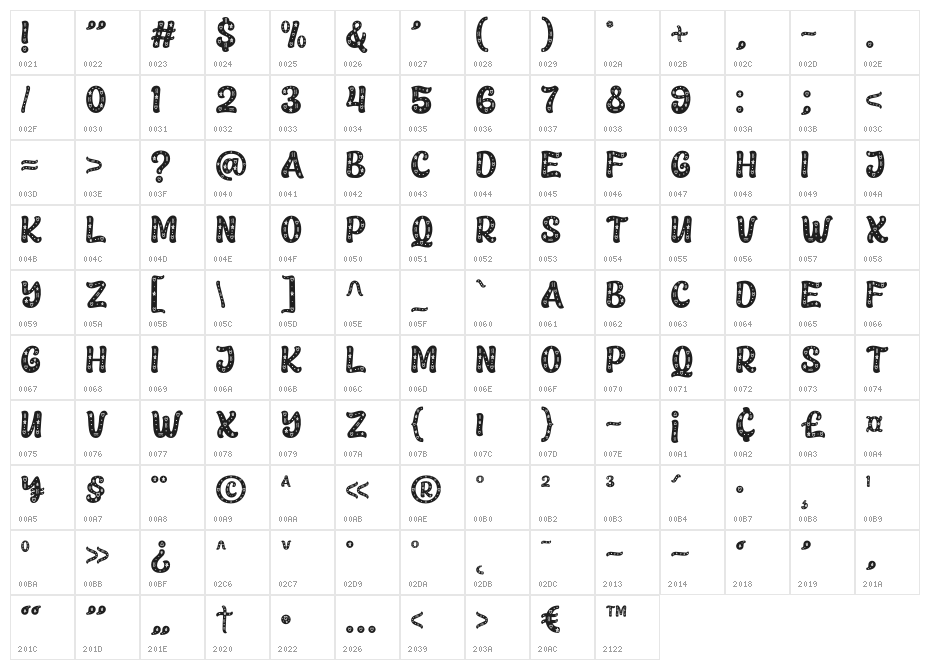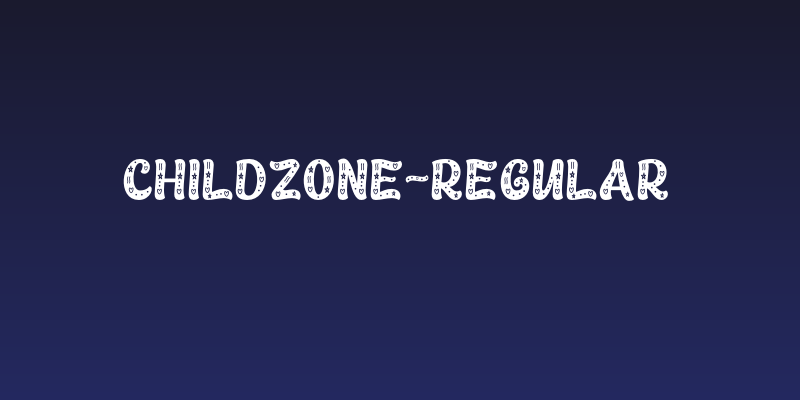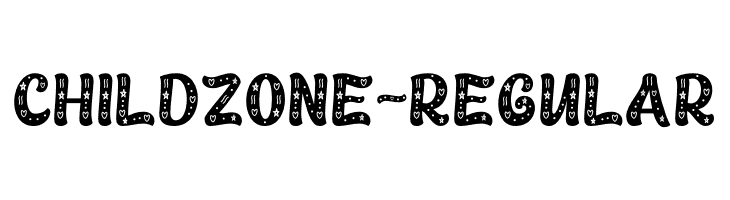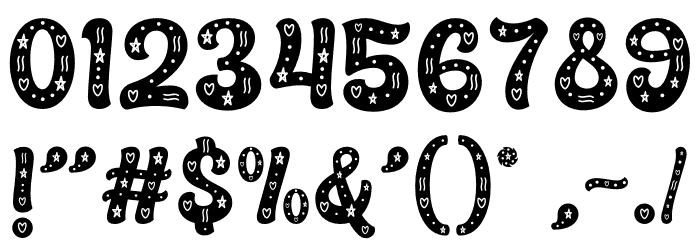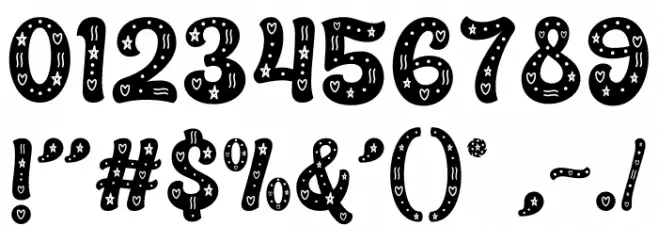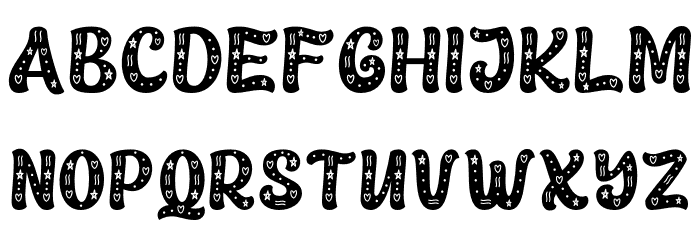
Childzone-Regular Font
| النمط العام | Playful, Whimsical |
| حالة الاستخدام | Headlines, Logos, Children's materials |
| مشاريع مقترحة | Ideal for children's books, toy packaging, birthday invitations, and playful branding. |